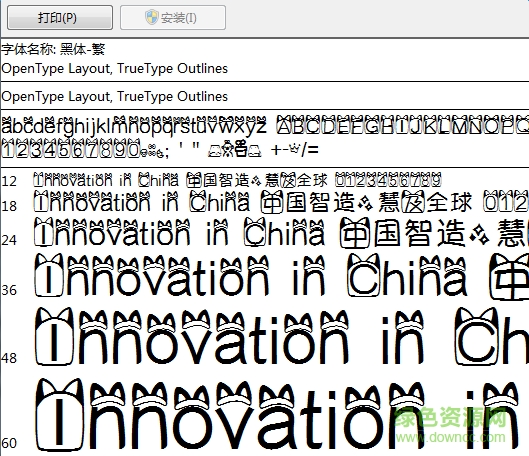
貓仔好萌字體是一款超好用的個(gè)性字體,該字體可以廣泛應(yīng)用于廣告設(shè)計(jì)、宣傳海報(bào)、ppt、影視制作以及任何使用文字的領(lǐng)域,有需要的朋友可以免費(fèi)下載收藏。
貓仔好萌字體是一款極具個(gè)性的字體,字體中穿插的小貓圖形,讓用戶能夠切實(shí)感受到萌意。有喜歡的朋友可以來綠色資源網(wǎng)下載使用!